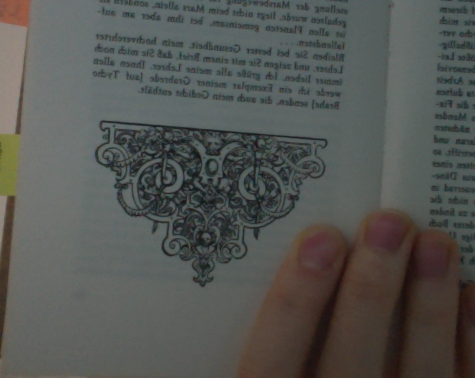
Wie nennt man solche Zierde am Ende von Kapiteln, etc ... ?
Gibt es einen Namen für solche Zierde an Kapitelenden oder ähnlichem? Wenn ja, wie heißt so etwas? Dieses hier ist aus dem wunderbaren Buch „Johannes Kepler, Leben und Briefe“ von Carola Baumgart.
Oder auch Schmuckzeichen, Zierstück oder Schlusslinie. Je nach Ausprägung und Größe.
Und nicht zu vergessen, das berühmte „Abteilungssternchen“